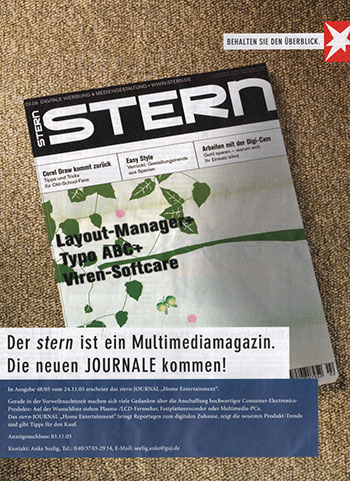
Au weiha, Magazin stern ...Der stern behauptet in einer Mimikry-Kampagne für die
Werbeindustrie, er sei – unter anderem – die Wirtschaftswoche,
Hör-zu und PAGE in einem. »Der Stern ist ein
Multimediamagazin« heißt es auf der ganzseitigen Anzeige, die eine
nachgemachte PAGE zeigt, mit »stern«-Schriftzug. Es ist zwar
verdienstvoll für beide Magazine, sich gegenseitig als Themenführer
darzustellen, aber PAGE kann es wirklich besser als der stern. Weiterlesen ...
![]() Der Stern behauptet, grafisch und typografisch so kompetent wie PAGE zu
sein, beweist jedoch genau das Gegenteil. Der im PAGE-Stil gestaltete Titelkopf
– umgetauft in stern – spottet jeder Beschreibung. Wer hier am Werk
war, hat nichts von Schriftentwerfen begriffen. Schon die Idee, aus dem
Original-P durch bloßes Hinzufügen eines Schrägstrichs mal eben
ein Versal-R zu machen erweist sich als Lachnummer. Die frei erfundenen
Buchstaben taugen auch nichts.